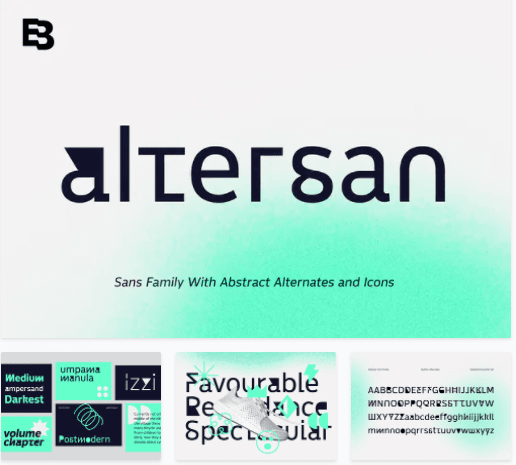
Altersan Font
Altersan - это семейство шрифтов без засечек с необычными абстрактными альтернативными глифами и значками. Первоначальный стиль - это гуманистический гротеск, который подходит для различных целей дизайна. Полная семья состоит из 8 стилей от тонкого до черного, с каждой подходящей косой. Он содержит 477 символов, охватывающих широкие латинские языки. Доступ к альтернативным глифам можно получить, активировав функцию opentype; Стилистические альтернативы, а также открыв панель глифов.